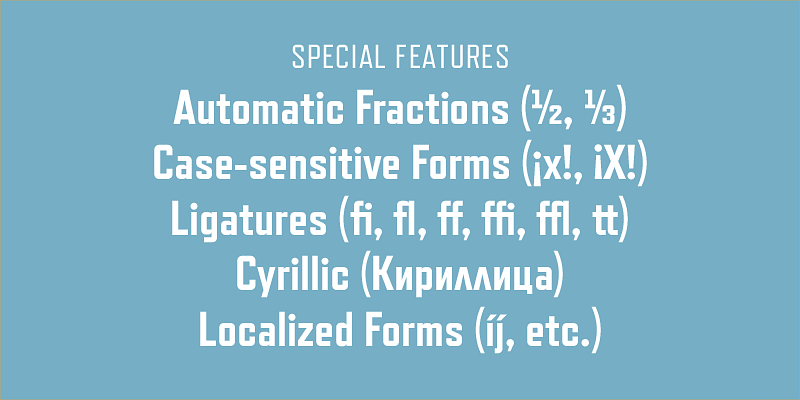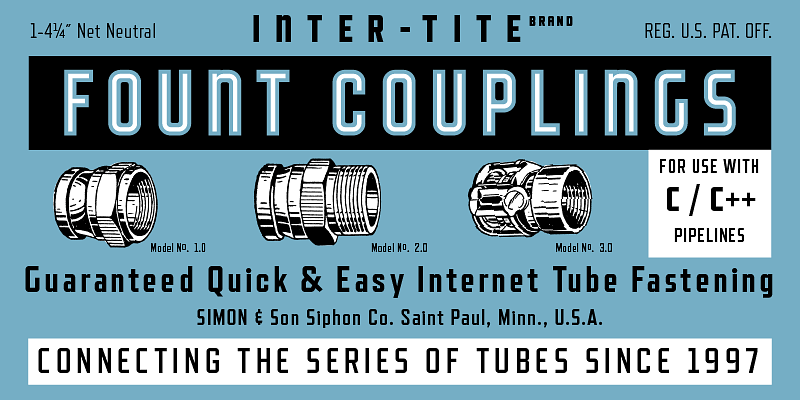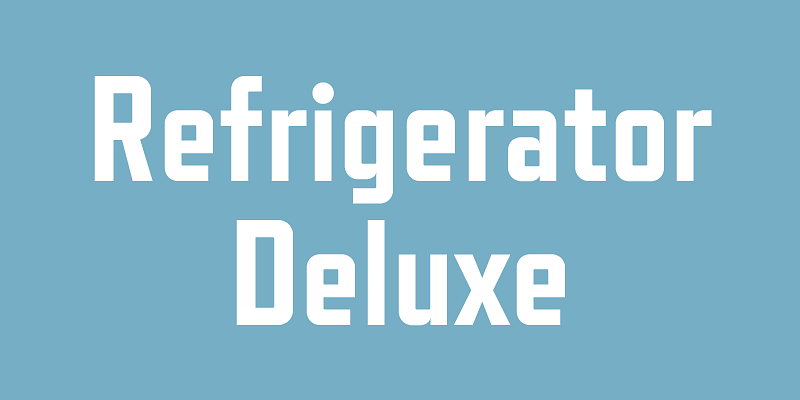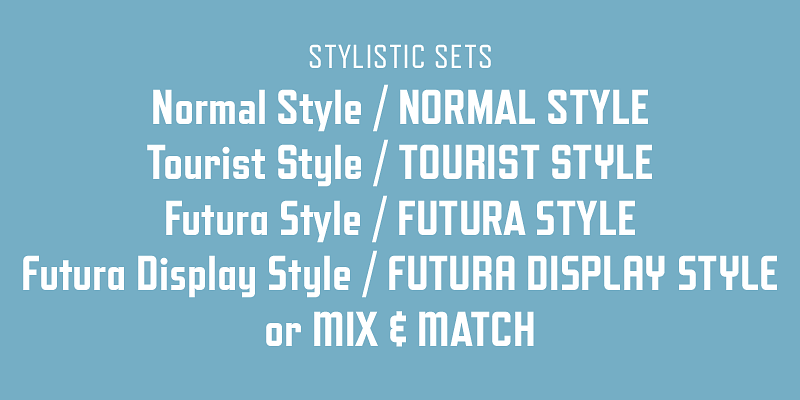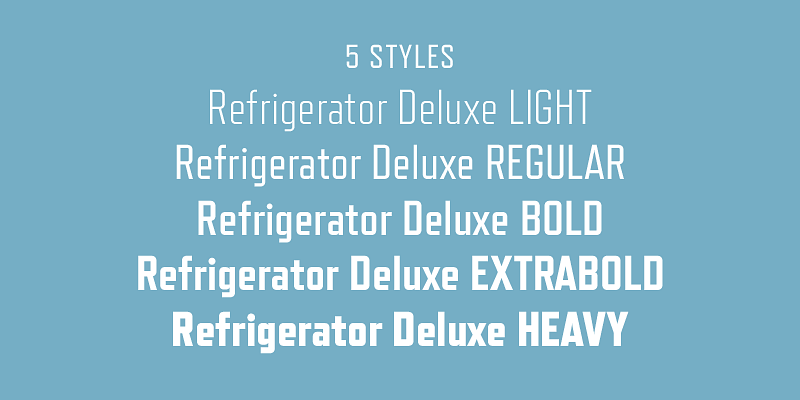
Refrigerator Deluxe (2008) si ispira al lettering generico a blocchi tipico della metà del XX secolo. Segue il tipico modello americano che si può vedere nei vecchi manuali di lettering, anche se l’ho disegnato puramente a memoria. Inizialmente l’ho pubblicato nel 2000 come Refrigerator, con il solo spessore Bold. Nel 2003 ho aggiunto Light e Heavy. Refrigerator Deluxe aggiunge un nuovo spessore (Regular) e una serie di caratteri alternativi che possono essere utilizzati per creare variazioni comuni dello stile a blocchi su cui si basa.